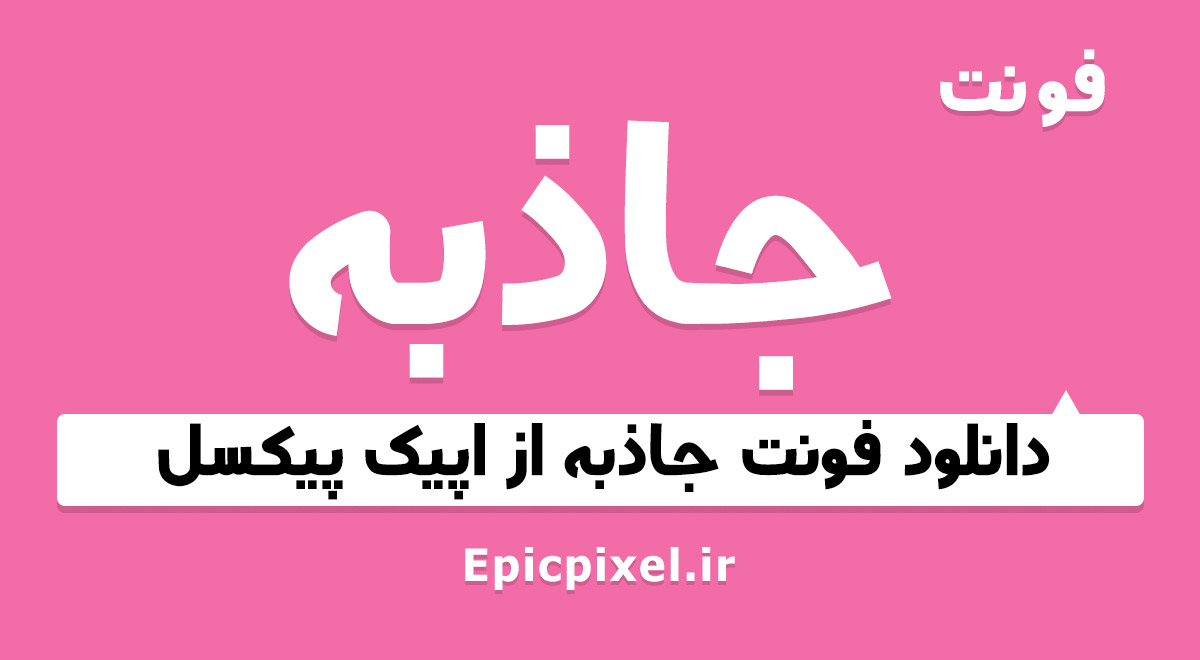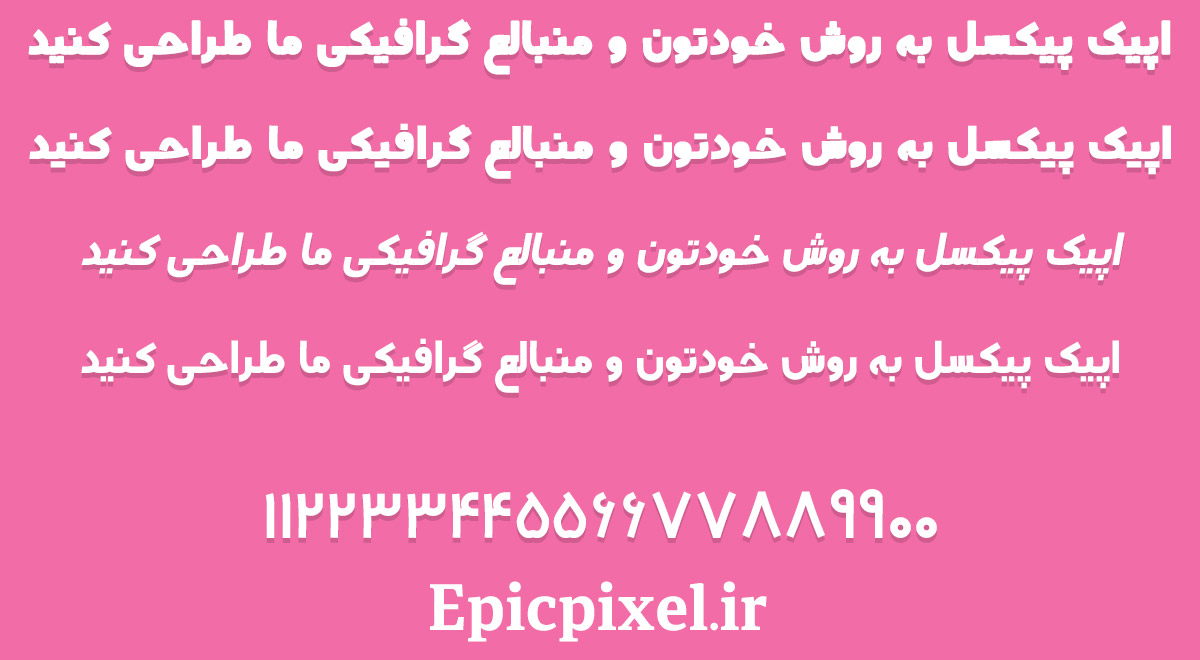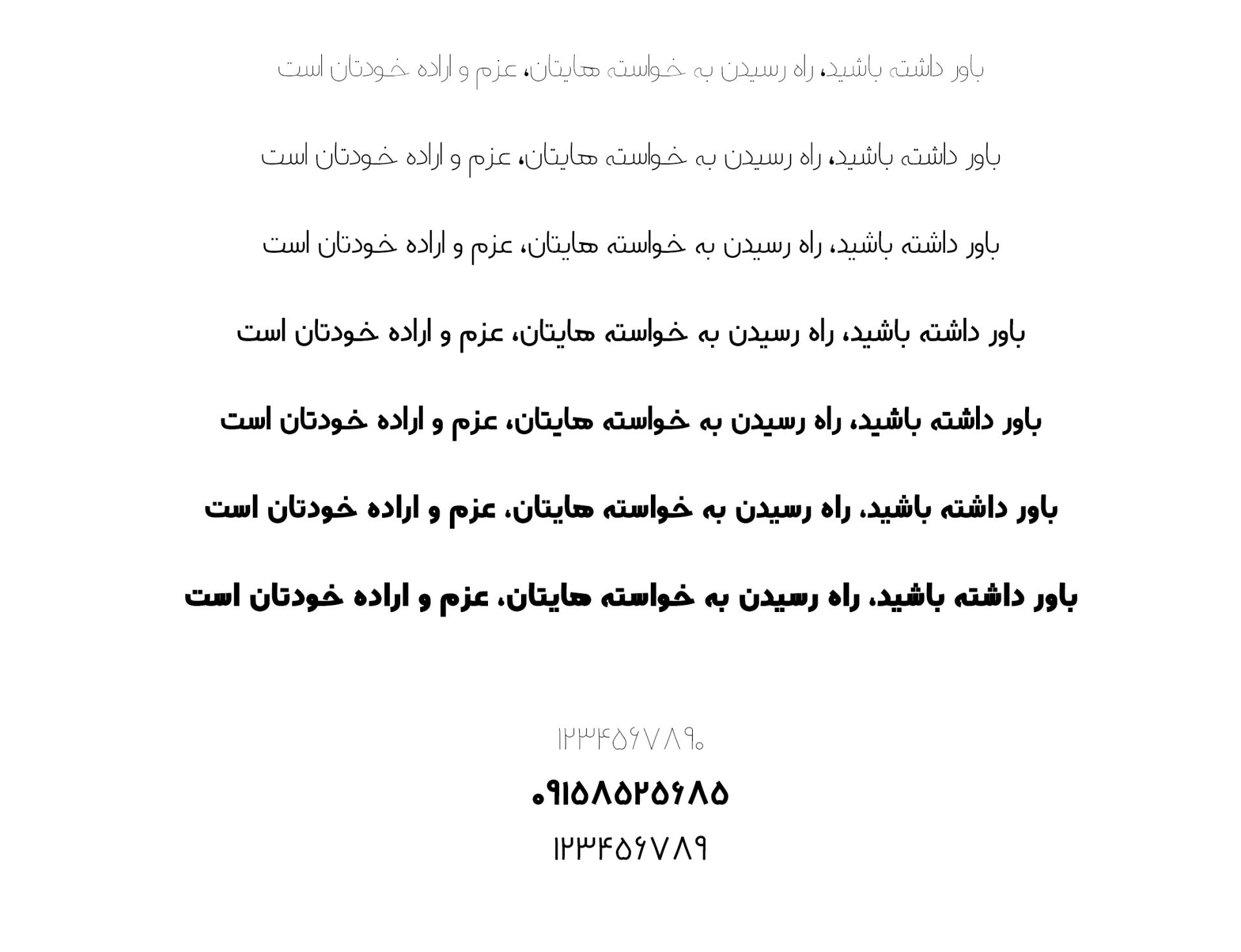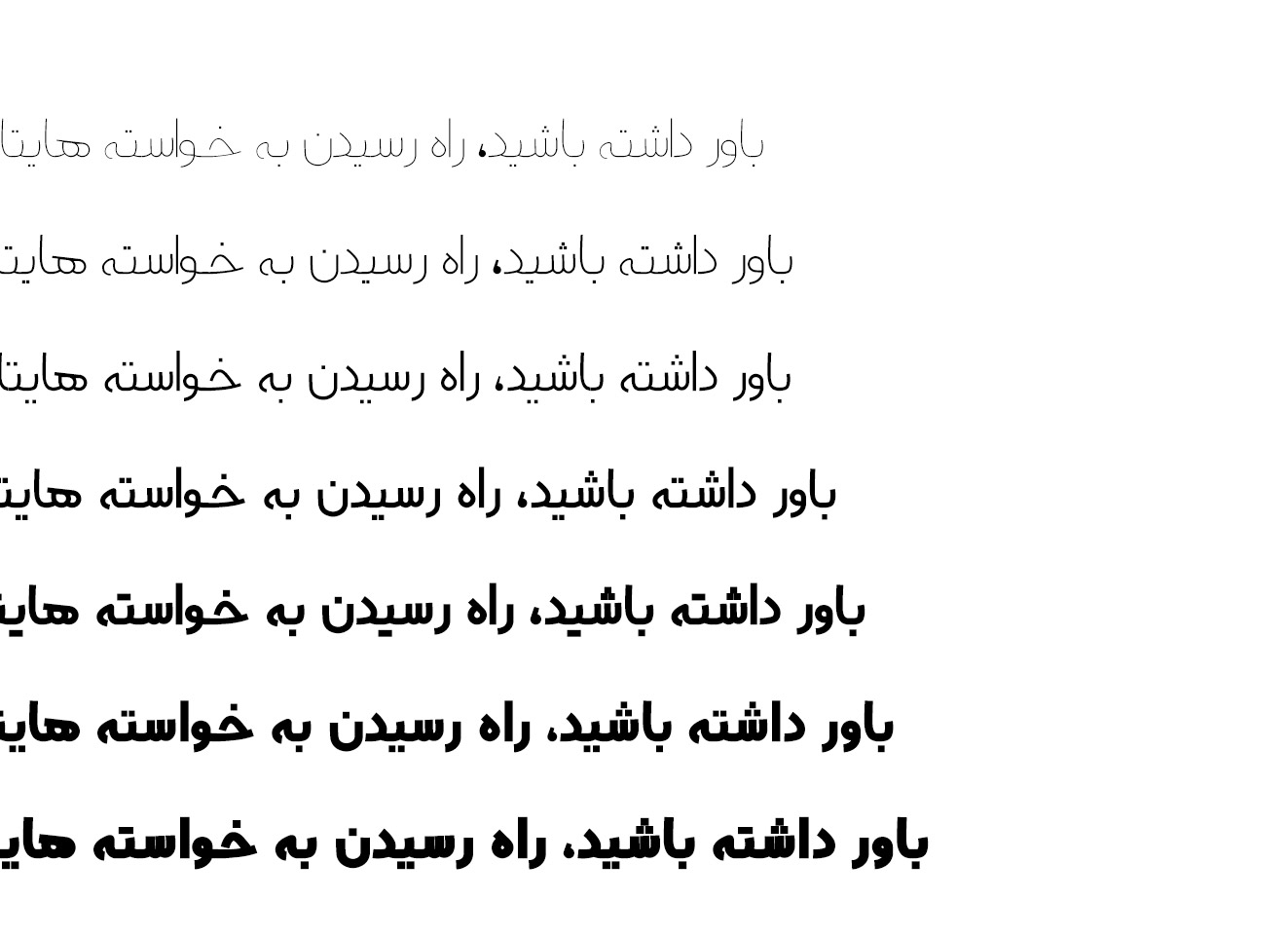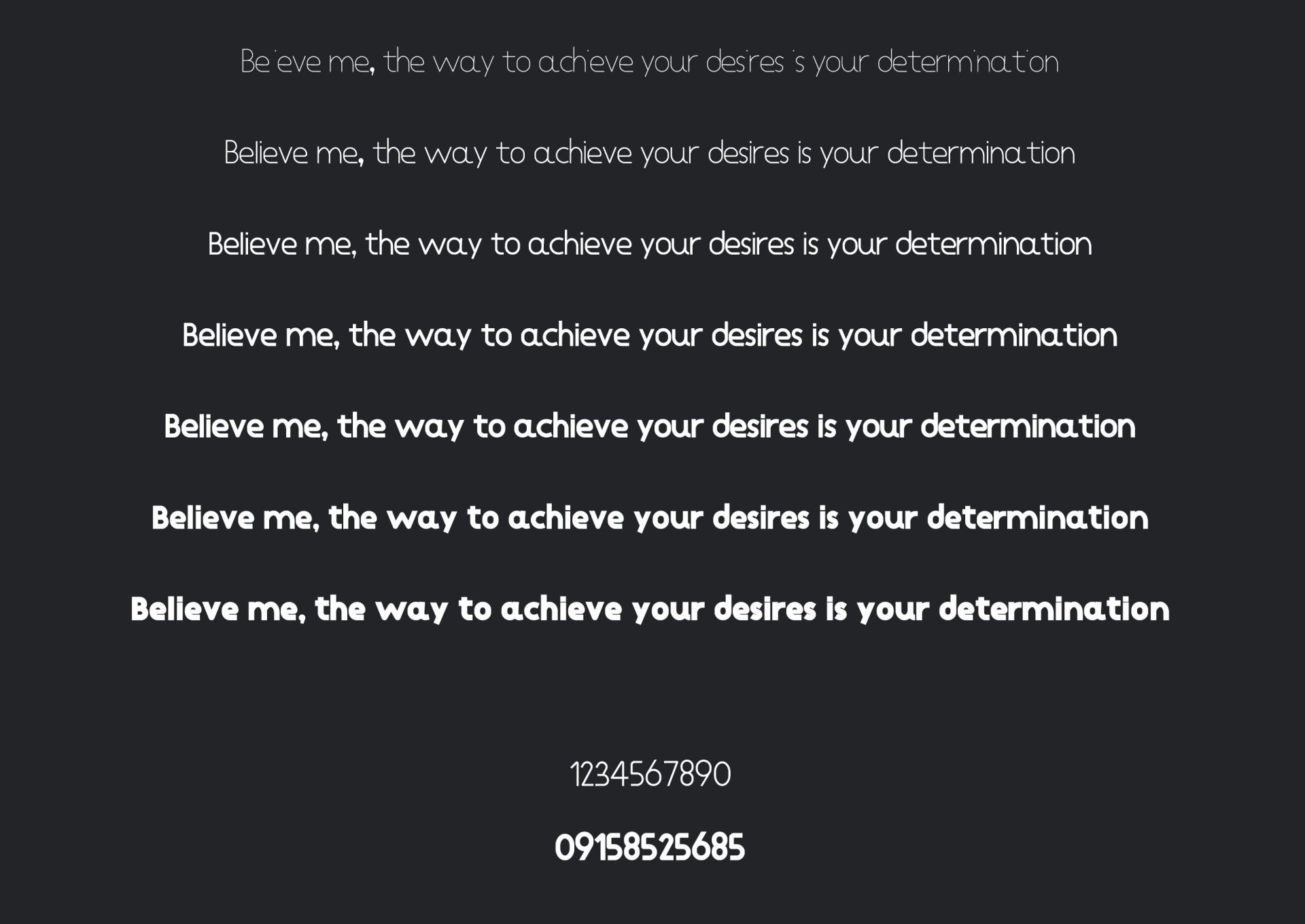
چرا فونت فارسی جاذبه را انتخاب کنیم؟ این فونت با طراحی خاص و چشم نواز خود، حسی از پویایی و در عین حال استحکام را به مخاطب القا می کند. خطوط این فونت، ترکیبی هنرمندانه از زوایای نرم و خطوط مستقیم است که هم در عناوین بزرگ و هم در متن های کوتاه، خوانایی بالایی دارد. این ویژگی باعث می شود طراحان بتوانند از جاذبه در طراحی های مختلف، از پوستر و لوگو گرفته تا صفحات وب و اپلیکیشن، به راحتی استفاده کنند.
یکی از نقاط قوت فونت جاذبه، وزن های متنوع آن است. این تنوع به طراحان امکان می دهد تا با استفاده از وزن های مختلف، سلسله مراتب بصری جذابی در طرح های خود ایجاد کنند و به متن ها عمق و جلوه ببخشند. با این حال، شاید بتوان گفت که تنوع بیش از حد وزن ها گاهی می تواند انتخاب را برای کاربر کمی دشوار کند.
«جاذبه» با وجود ظاهر مدرن و امروزی اش، ریشه هایی در خوشنویسی سنتی فارسی نیز دارد. این ترکیب سنت و مدرنیته، به «جاذبه» هویتی منحصربه فرد بخشیده که آن را از سایر فونت های فارسی متمایز می کند. اگر به دنبال فونتی هستید که هم زیبا و چشمگیر باشد و هم حس اصالت و هویت را منتقل کند، «جاذبه» می تواند انتخاب بسیار مناسبی برای شما باشد. این فونت با ظاهر جذاب و کاربردی خود، به نوشته های شما جان می بخشد و آن ها را برای مخاطب دلنشین تر می سازد.